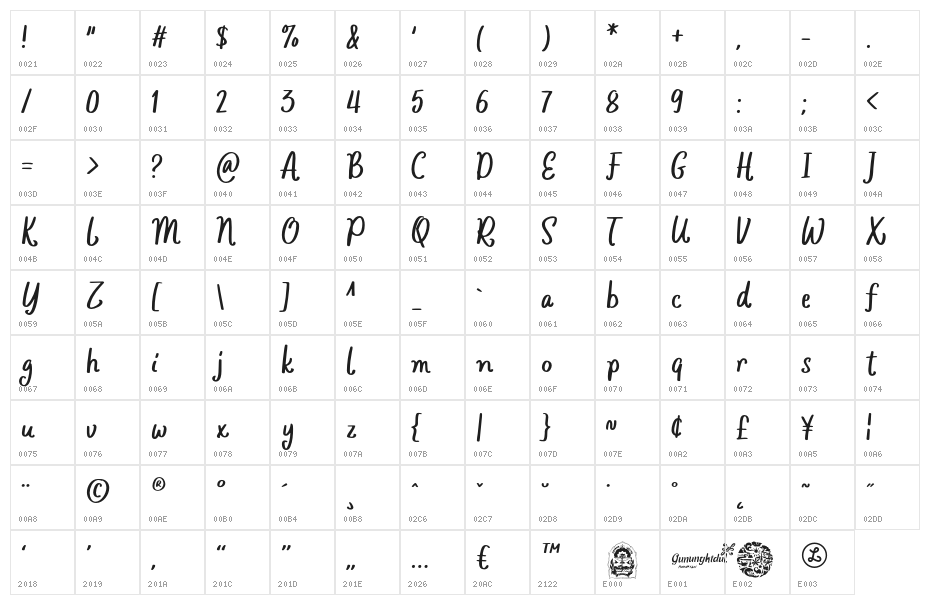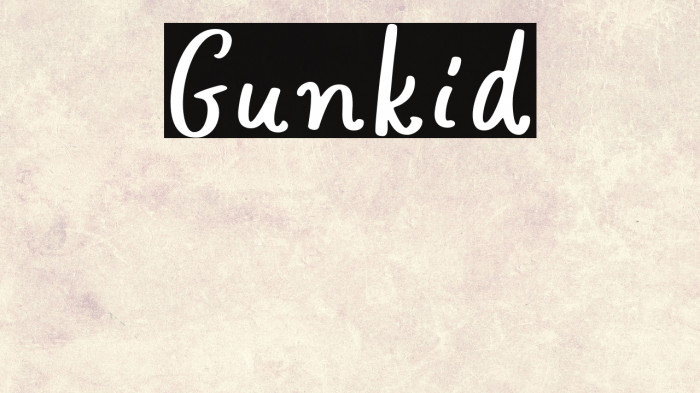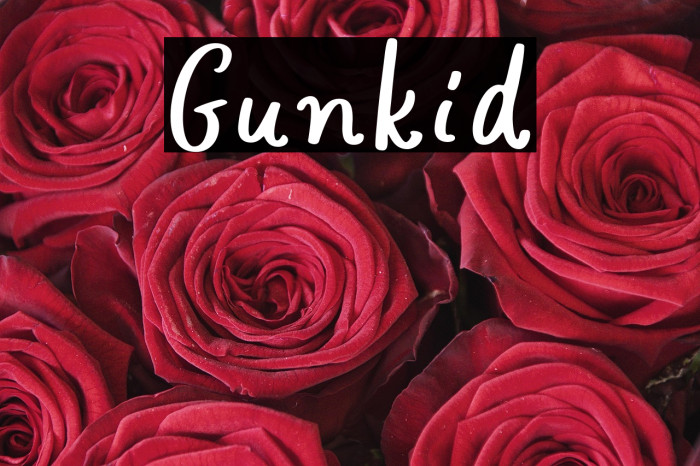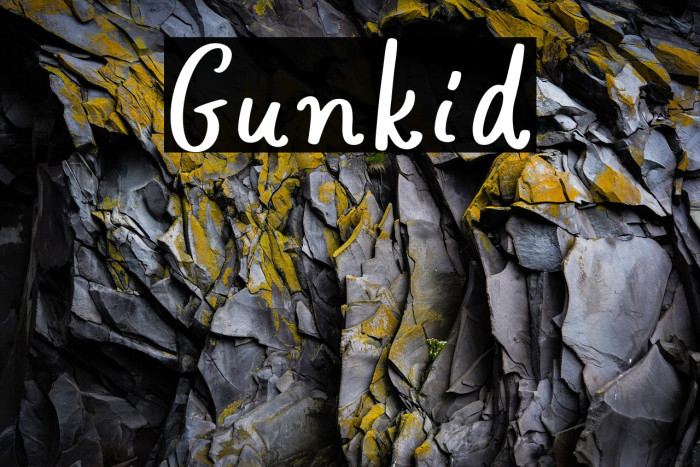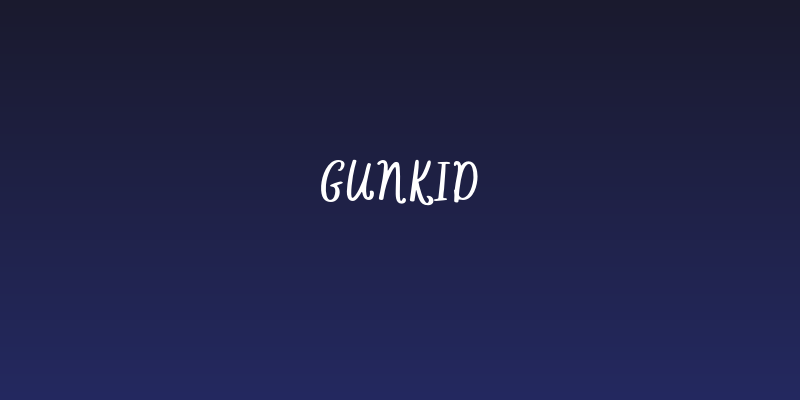
Gunkid Font
| Stile generale | Casual, Handwritten |
| Caso d'uso | Logos, Invitations, Greeting Cards |
| Progetti proposti | Ideal for greeting cards, invitations, personal branding, and creative projects that require a friendly and approachable touch. |